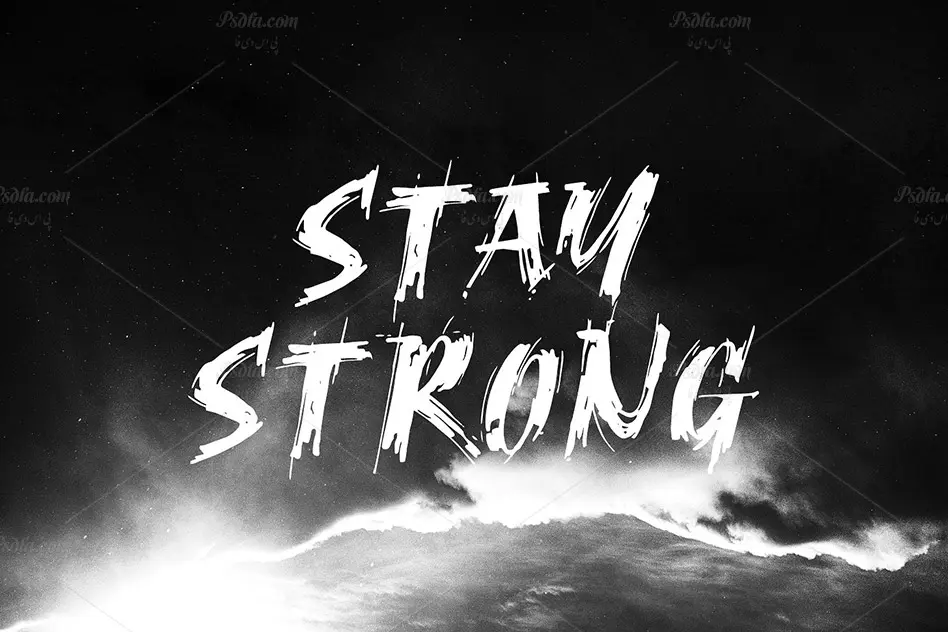
فونت انگلیسی و قلمویی Ragnar مناسب برای طراحی پوستر
فونت انگلیسی و قلمویی Ragnar
در این مطلب شاهد فونت انگلیسی و قلمویی Ragnar مناسب جهت استفاده در طرح های گرافیکی به خصوص طراحی انواع پوستر می باشید. این فونت زیبا در قالب یک فایل otf بر روی سایت بارگذاری شده است که با نصب این فایل در پوشه فونت های سیستم قادر به استفاده از آن در تمام نرم افزارهای گرافیکی و یا ویرایشگر متن از جمله نرم افزار فتوشاپ ، مجموعه نرم افزار آفیس و … خواهید بود. فونت Ragnar در وزن معمولی (Regular) و به صورت Alt یا حروف بزرگ طراحی شده است که از آن می توان در طرح های گرافیکی همچون طراحی انواع پوستر ، بنر ، تراکت ، بروشور و … استفاده نمود.